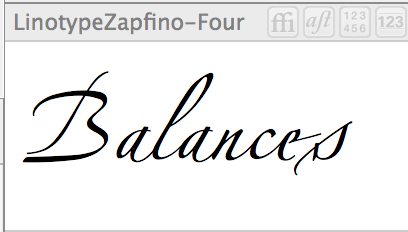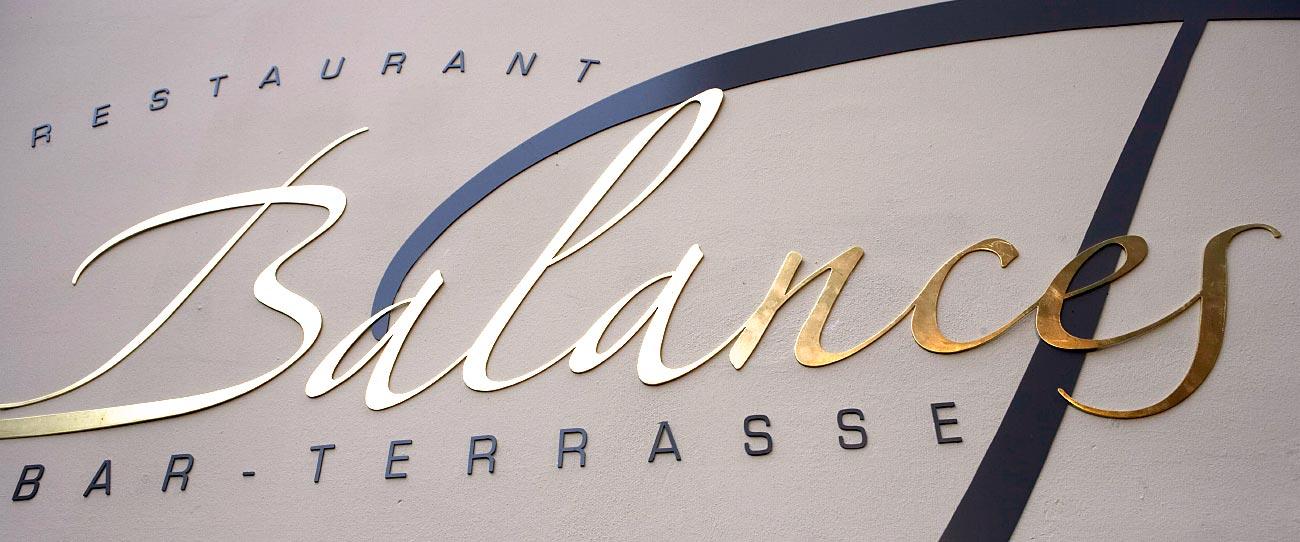
Suche ewigs diese Schrift (Balances)
Habe sie an einer Hotelfassade gesehen und mich verliebt. Vorallem das B hat es mir angetan. Kennt ihr die Schriftart oder ähnliche?
Das ist die Linotype Zapfino und zwar in der Variante Four.
Die Schrift verfügt über unglaubliche Mengen an Alternativbuchstaben, das siehst Du hier zum Beispiel am e und am s – da sind andere Varianten zu sehen.